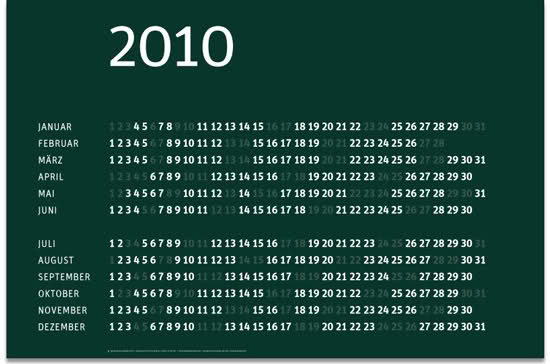
Wieder da: der Typografische Kalender (mit Quiz)
Auch das nächste Jahr ist gerettet: Alle, die einen wirklich reduzierten Wandkalender suchen und bei der Typografie keine Kompromisse machen wollen, können aufatmen. Der Typografische Wandkalender ist wieder da. Das ganze Jahr im Flattersatz, FF Unit mit Tabellenziffern, mehr nicht. Weniger nicht.
Mini-QUIZ
Für alle Typofreunde im Forum hier habe ich noch ein kleines Quiz vorbereitet. Der Bildausschnitt zeigt ein Detail einer Schrift aus einem anderen Lernplakat. Wie heißt die Schrift und von wem ist sie. Die erste richtige Antwort gewinnt einen Typografischen Kalender 2010.
fast, es ist ein Detail von einem »n«.
VistaSans von Xavier Dupré?
Warum das Fragezeichen? :-)
Weil ich so tun wollte als ob das schwer gewesen wäre :hammer:
Ich hab mir schon gedacht, dass das keine Herausforderung ist :-)
Vista Sans ist richtig, Xavier Dupré auch. Bertel, schick mir bitte eine PN mit einer Postadresse.
Das war insofern nicht schwer als dass ich mich an dein Wildpflanzen-Lernplakat erinnert habe. Dann musste ich hier nur noch danach suchen … :D
Die Auflage ist geliefert worden und sieht prächtig aus. Mein Büro riecht wieder nach frischen Drucken und ein weiteres Fach im Papierschrank ist belegt. Pomeranz: Du bekommst den allerersten, dann gehen die Vorbestellungen raus.
Oh ja, sieht wirklich prächtig aus. Der Kalender kam heute an und ist eine Zier. Danke nochmal!